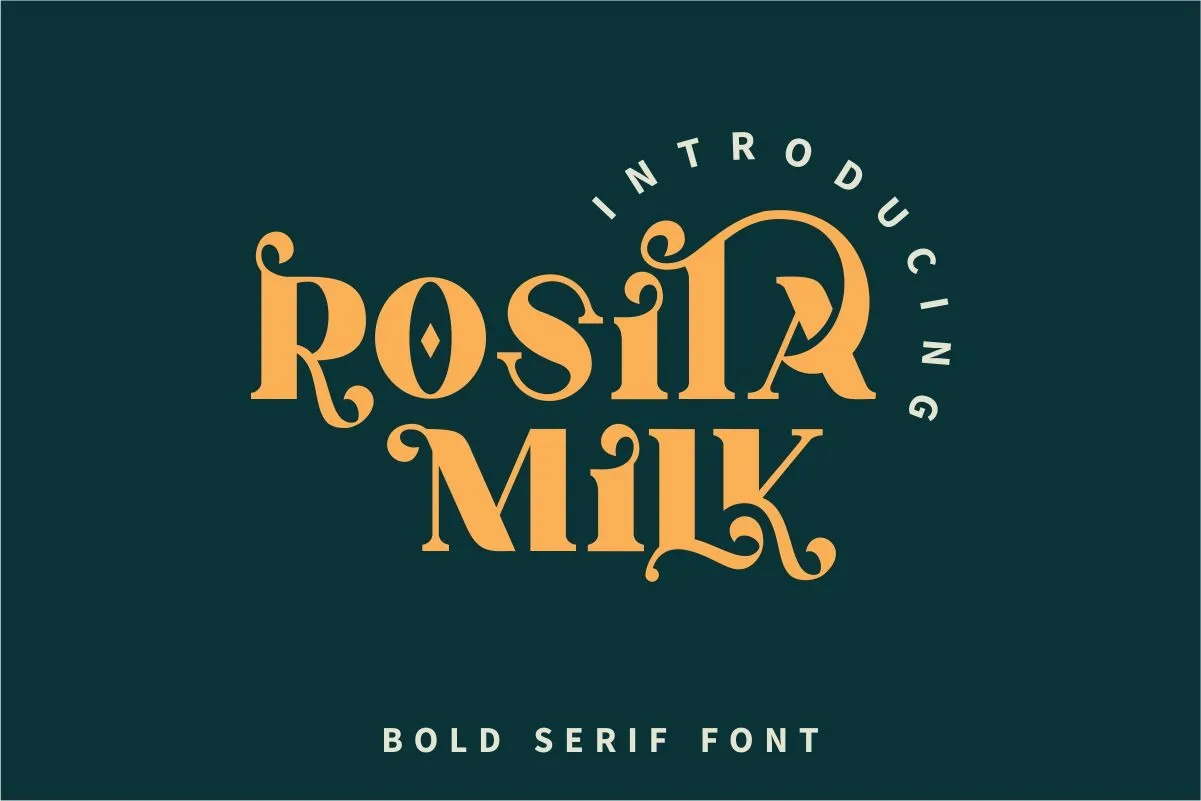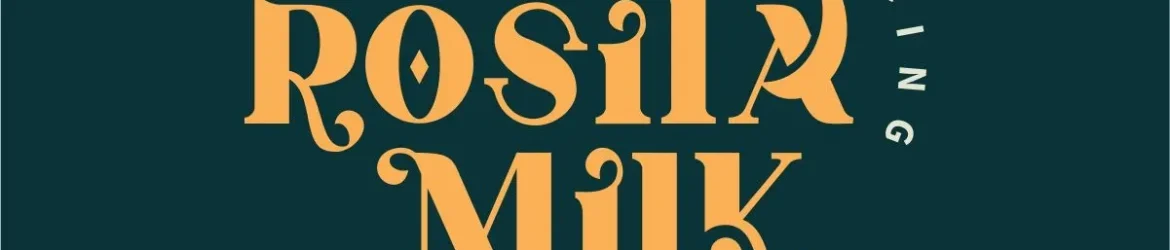
A Rosita Milk Font é uma escolha perfeita para quem busca estilo e elegância no design visual. Esta serif moderna apresenta traços robustos que garantirão um toque de sofisticação a qualquer projeto, seja ele gráfico ou editorial. Com muitas alternativas disponíveis, essa fonte se destaca ainda mais em presentes de casamento, convites, embalagens de produtos e identidades visuais inovadoras. Seja para apresentações, marcações de água ou designs promocionais, a Rosita Milk é uma escolha ideal que trará uma personalidade única aos seus projetos. Além disso, ela faz uma ótima combinação com outras serifas mais tradicionais e modernas, tornando-a uma fonte versátil para uma variedade de aplicações e cenários.